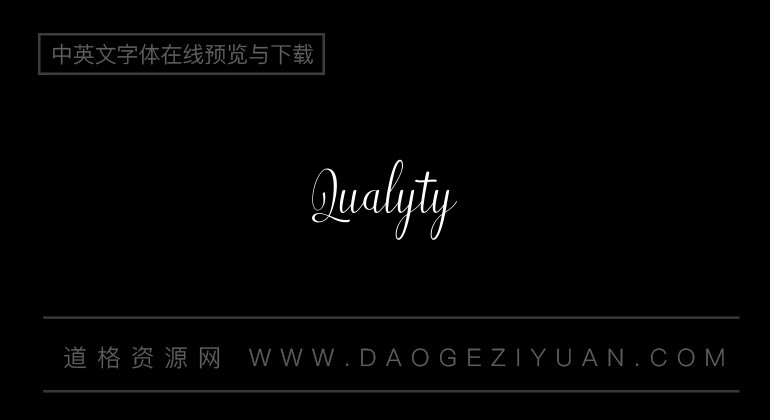
? Qualyty 字体是一款由英国设计师 Tom Anders Watkins 设计的新字体,它具有鲜明的现代感和清新的外观,可以帮助您的设计项目脱颖而出。Qualyty 字体的特点是它的粗细变化和曲线,可以帮助您增加设计的视觉吸引力。Qualyty 字体还有几种字重,可以满足您的不同需求。内容介绍
Qualyty是一款非常不错的手写艺术字体,具有很好的视觉感,适合于文化类的宣传设计、商业类品牌的广告和产品包装设计以及个性化文字排版等较多场景。